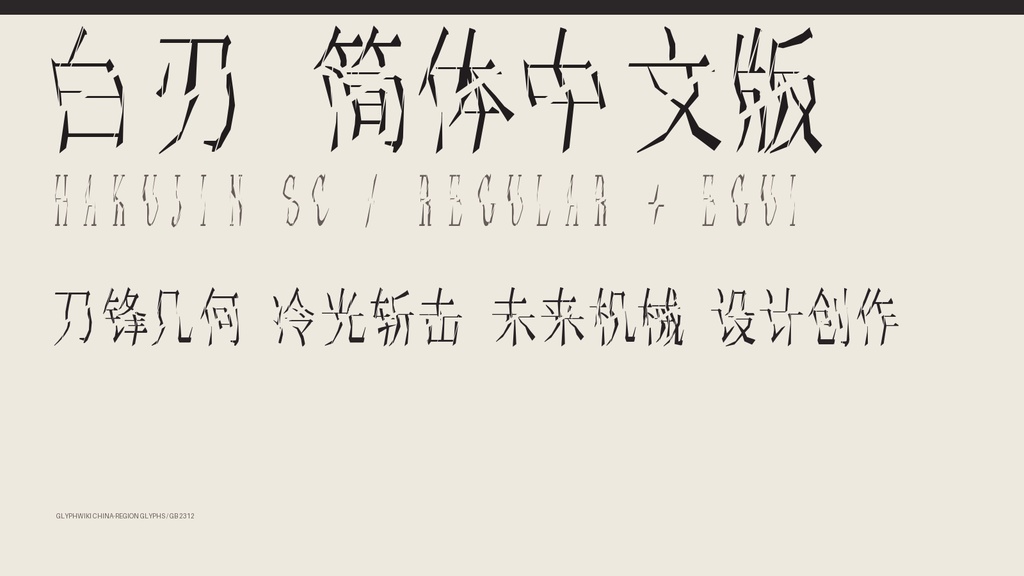
白刃 SC|简体字6,763字・2款字体
【白刃 SC / HAKUJIN SC】 笔画如同被锋利刀刃切开,几何缺口、中心沟槽与斜向斩击贯穿字面。 这是一套带有冷光金属感的简体中文赛博展示字体。 Regular 保持清晰而锐利的基本结构,Egui 则强化切口和攻击性的尖锐轮廓。 ■ 价格 1,480日元 ■ 内含字体 ・Regular:锐利但较易识读的标准版 ・Egui:切口更深、轮廓更具攻击性的强化版 ■ 格式 TrueType(TTF)2款 / Windows・macOS ■ 收录 每款共7,542个字码(包含空格) GB 2312 全部汉字:6,763字 拉丁字母、数字、半角与全角符号:779个 ■ 特点 ・刀锋般的斜切面与几何缺口 ・贯穿笔画的中心沟槽 ・汉字、英文字母、数字和符号采用统一的切割规则 ・Regular / Egui 两种锋利程度 ■ 推荐用途 赛博朋克、动作游戏、科幻UI、战斗标题、音乐封面、影视字幕、海报、直播画面、品牌标志与角色名称 ■ 使用许可 可用于个人及商业项目。可用于标志、视频、游戏、印刷品、直播素材、同人及商业作品。 无需署名。禁止重新分发、共享或转售字体文件。 详细条款请查看ZIP内的使用许可。 ※含有细长沟槽与尖锐切口,推荐用于28px以上的标题。